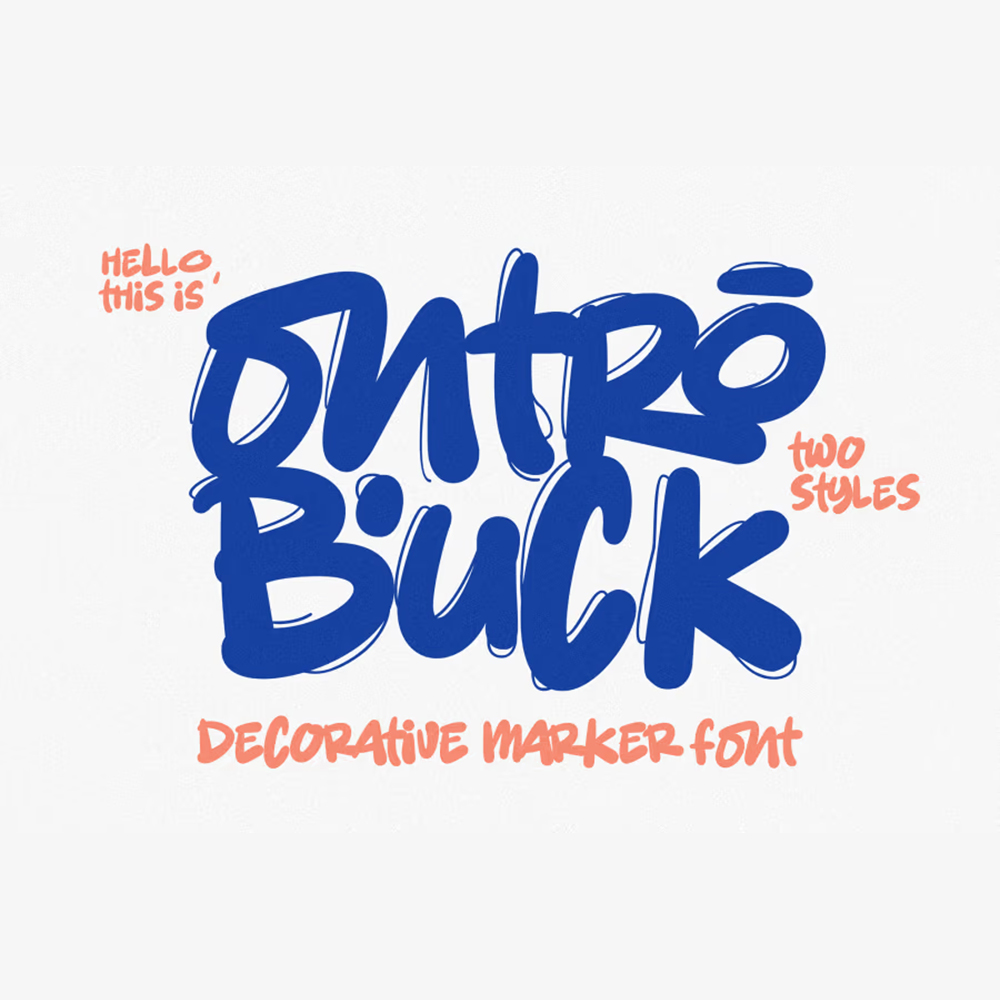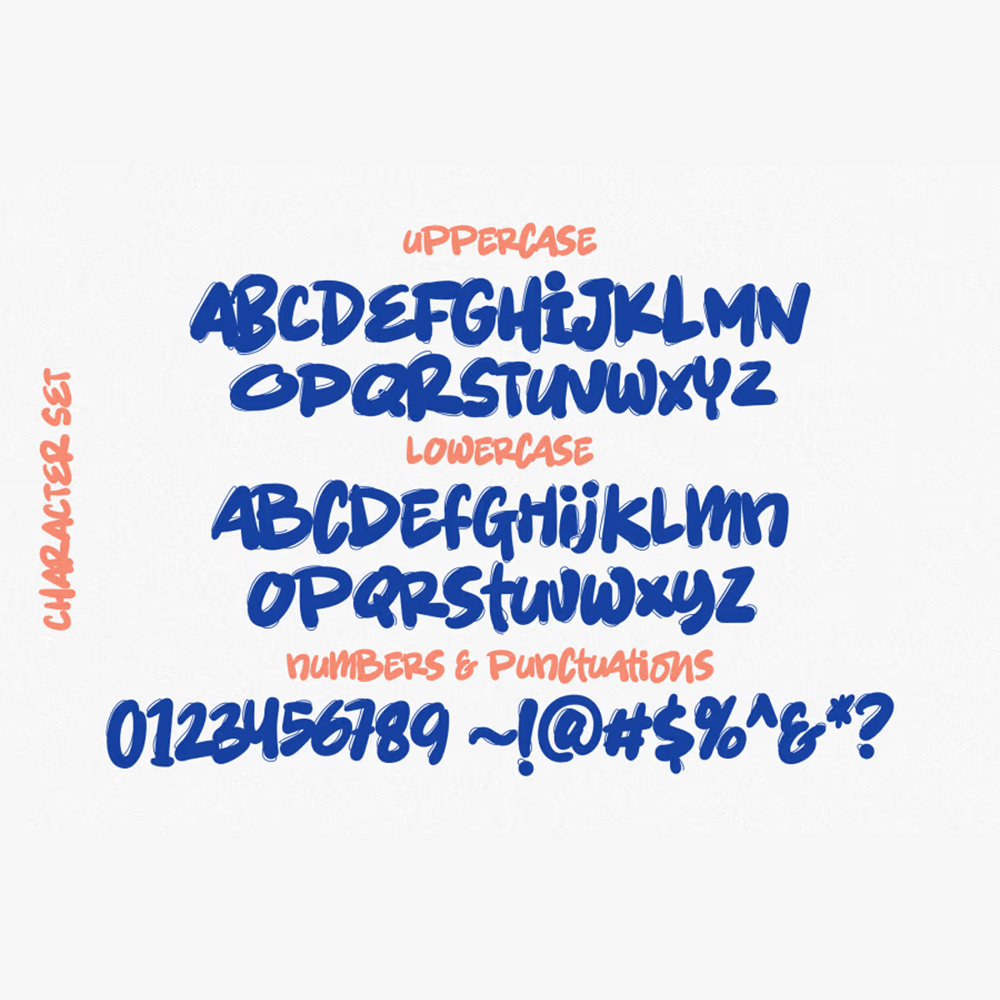
فونت پرمیوم و انگلیسی Ontro Buck Font جوهره خطوط ماژیک دستی را به تصویر می‌کشد و زیبایی‌شناسی جسورانه و پویایی را ارائه می‌دهد. هر حرف با دقت ساخته شده است تا حس خودانگیختگی و خلاقیت را منتقل کند و آن را برای طرح‌هایی که توجه را می‌طلبند، ایده‌آل می‌سازد. Ontro Buck یک فونت تزئینی بی‌نظیر که پروژه‌های خلاقانه شما را با ضربات جسورانه و رسا و یک ذوق هنری منحصر به فرد القا می‌کند. Ontro Buck که برای برجسته شدن طراحی شده است، برای کسانی که به دنبال ایجاد تأثیر بصری قوی با تایپوگرافی خود هستند، عالی است. همچنین برای پوسترها، تراکت‌ها، برندسازی و موارد دیگر ایده‌آل است، تضمین می‌کند که پیام شما با لمسی قدرتمند و هنری منتقل می‌شود.
• گلیف های استاندارد
• فونت انگلیسی آنلاین عددی و عملکردی
• فونت انگلیسی برای لوگو جایگزین و لیگاتور